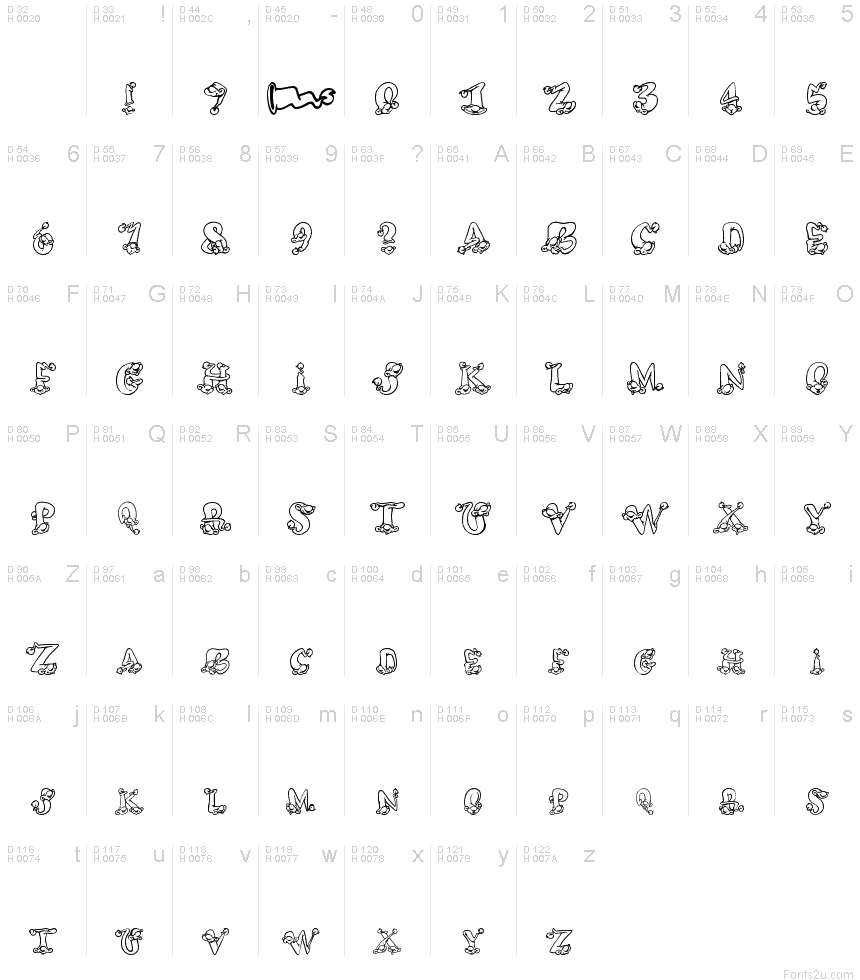
Alpha Elfin من Beeline Fonted by Miss Claude هو خط عرض مجاني برسوم كرتونية، يبدو وكأنه مكتوب بأحذية أقزام صغيرة وملتوية. كل حرف هو عبارة عن خط خارجي حيوي، يتميز بالحلقات والالتواءات والنتوءات المرحة والزوايا الناعمة، وكأنه خُطّ بحبر أسود على هامش إحدى قصص الخيال. الأشكال الهوائية المفرغة تجعله خفيفاً وسهل القراءة مع الحفاظ على طابع غني، مما يضفي على العناوين لمسة سحرية مرسومة يدوياً كأنها من غابة خيالية.
باستخدام Alpha Elfin، يمكنك تحويل عناوين كتب الأطفال، ودعوات الحفلات الخيالية، وبطاقات الأعياد، وشعارات الألعاب، وملصقات الفصول الدراسية، أو أغلفة المنتجات اليدوية فوراً إلى تصميمات فريدة تحكي قصصاً. يتألق هذا الخط المجاني عند استخدامه بحجم كبير وخط عريض، حيث يمكن لكل تلك التجعيدات الغريبة أن تتنفس. بالنسبة للنص الأساسي، قم بمزجه مع خط بلا زوائد (sans serif) ذي زوايا دائرية، واترك Alpha Elfin يتولى مهمة إبراز الكلمات السحرية التي تخطف الأنظار.